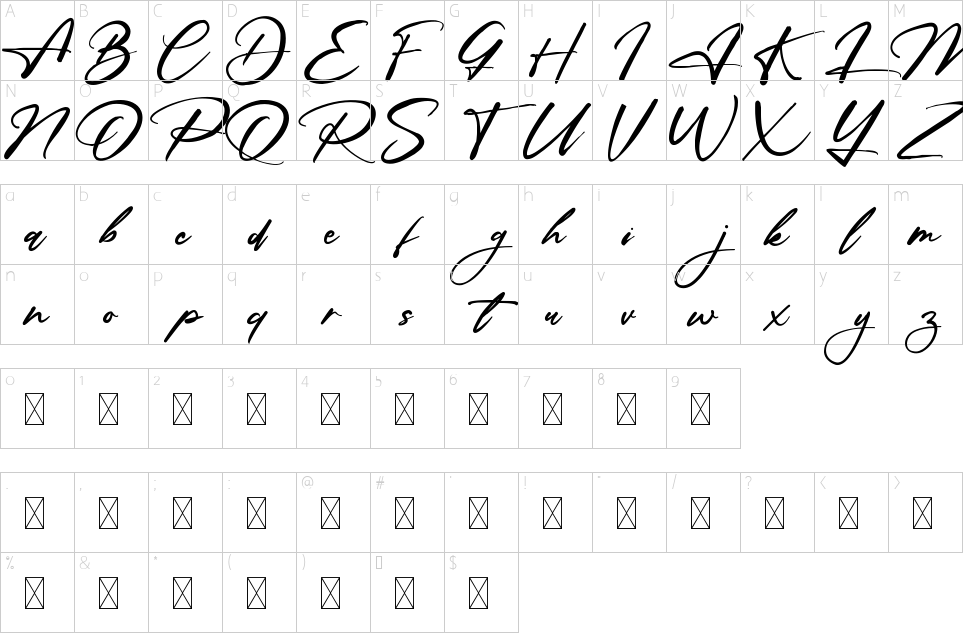
A Prologie Signature é uma fonte criada pela Muwatta Studio, disponível gratuitamente tanto para Windows quanto para Mac. Suas linhas elegantes e modernas tornam-a uma escolha perfeita para qualquer projeto que valorize sofisticação e originalidade. Com apenas 766 downloads registrados, é evidente que esta fonte se destaca, oferecendo uma experiência única e única em seu gênero. Seja você um designer profissional ou iniciante, a Prologie Signature se destaca como uma fonte de qualidade que vai enriquecer seu trabalho, adicionando um toque único e inovador a qualquer projeto. Não perca essa oportunidade de adquirir a Prologie Signature e dar um toque de personalidade a seus projetos digitais.